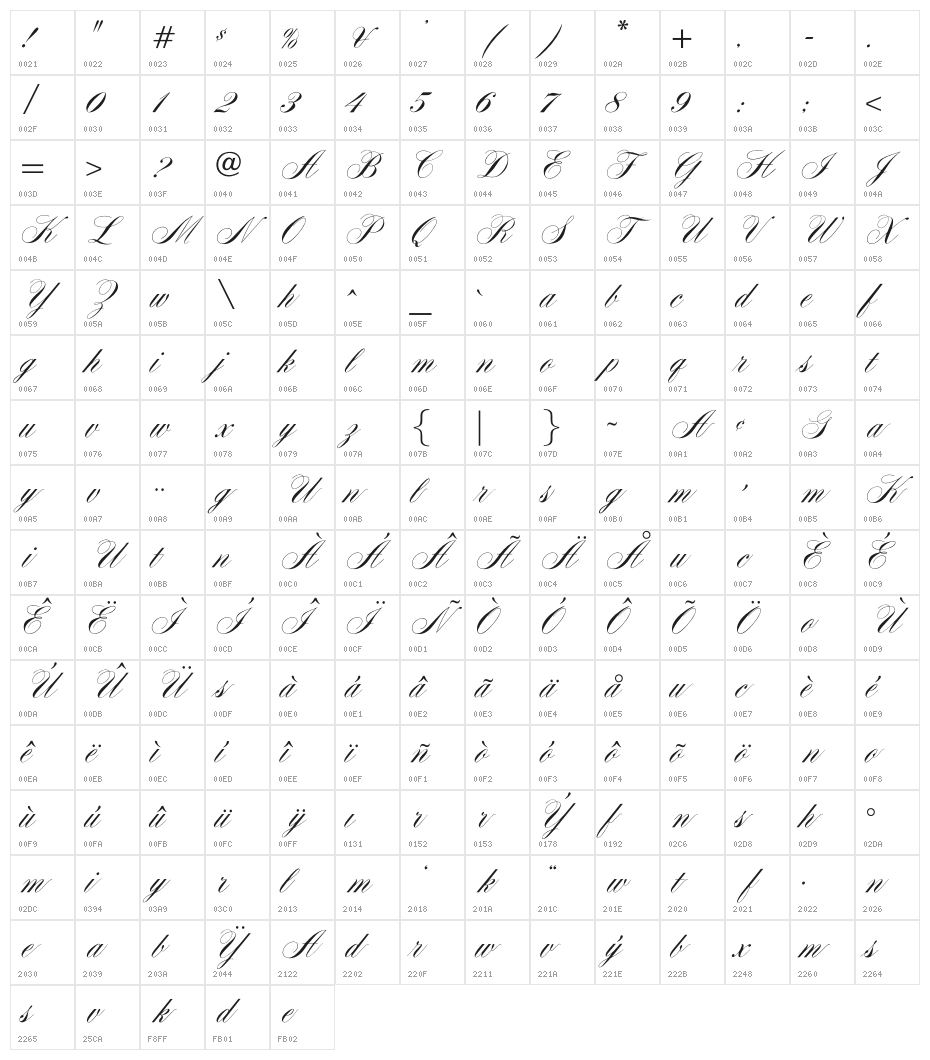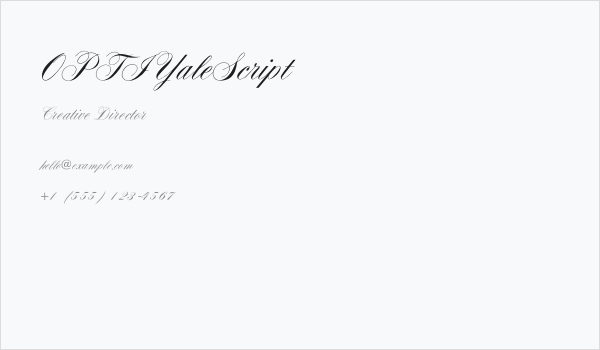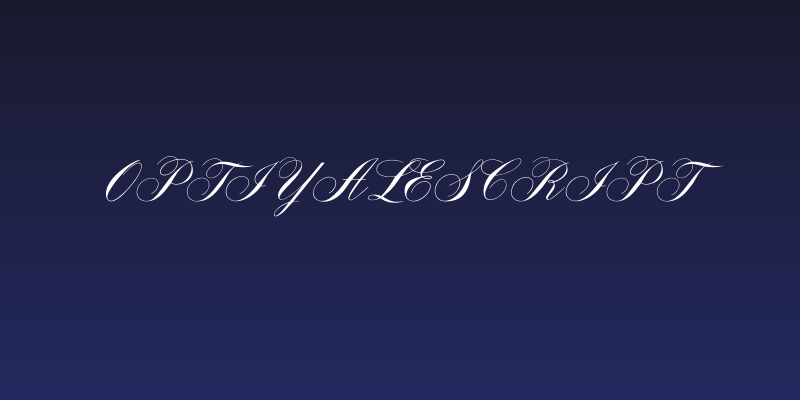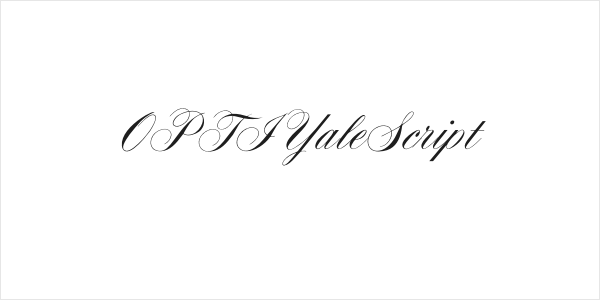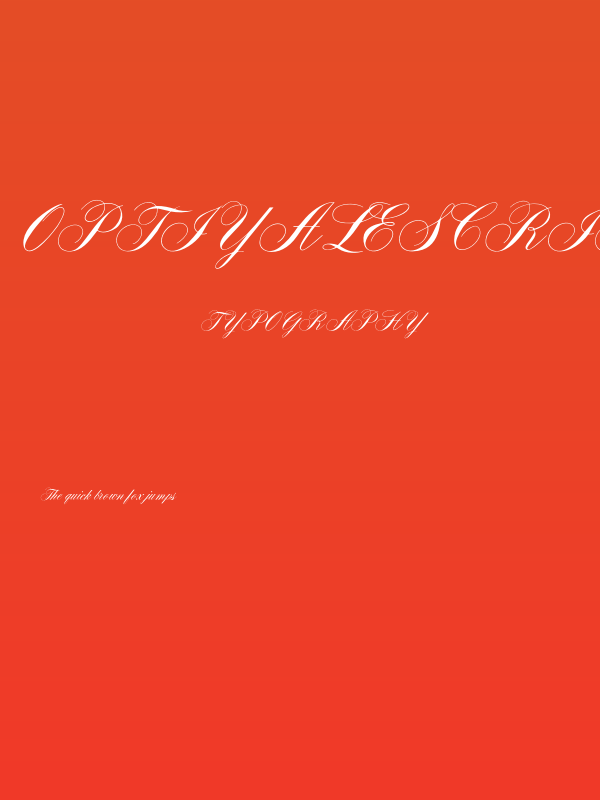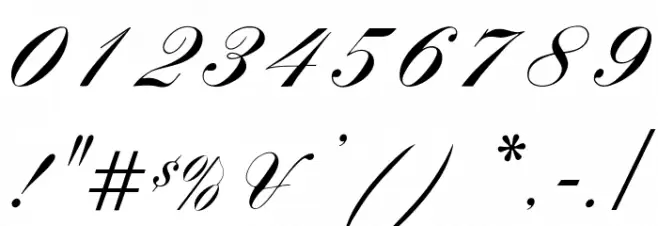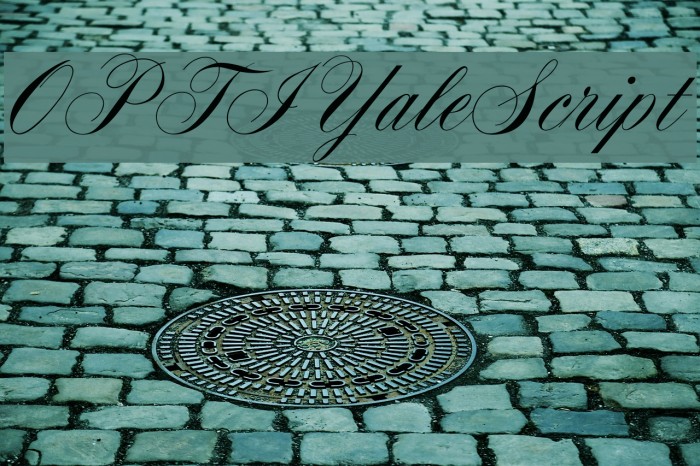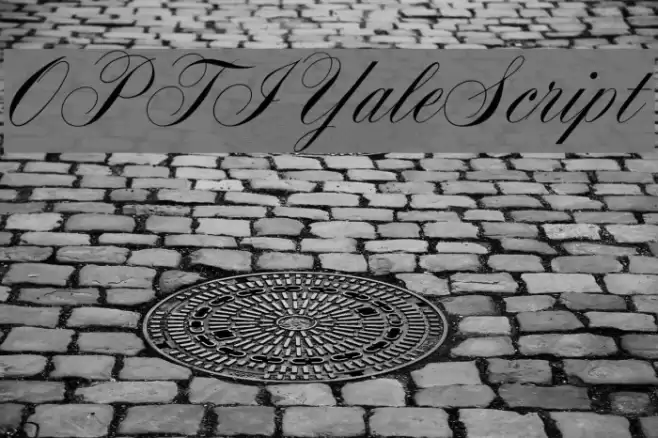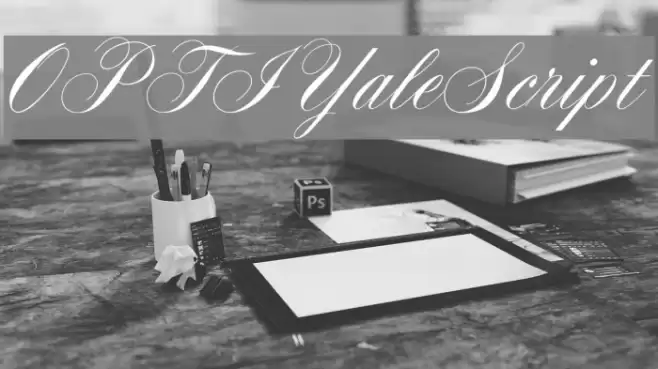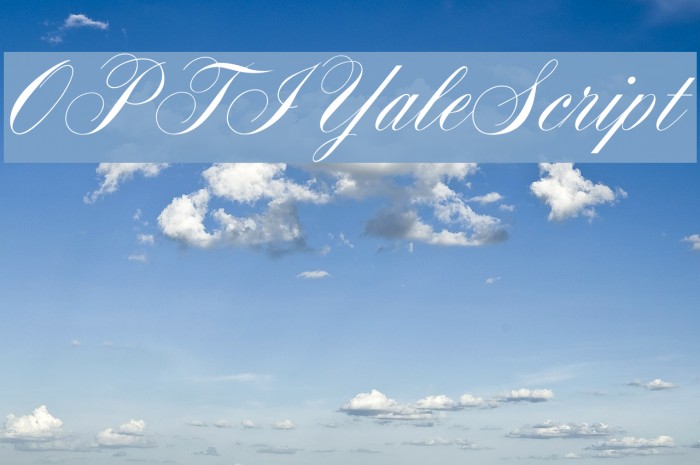
OPTIYaleScript Font
✎ Script
| Kategorien | Script |
| Gesamtstil | Classic |
| Anwendungsfall | Logos, Invitations, Decorative text |
| Vorgeschlagene Projekte | Ideal for wedding invitations, elegant branding, formal event programs, and luxury product packaging. |